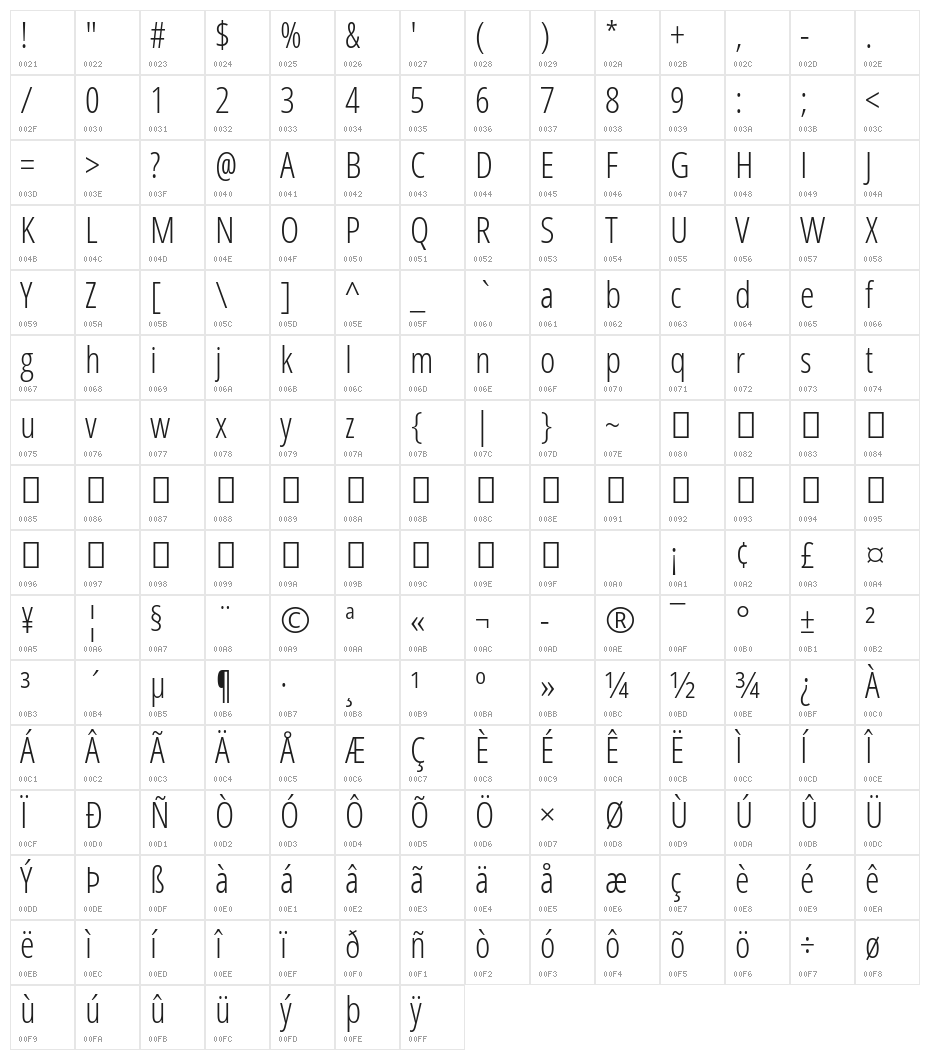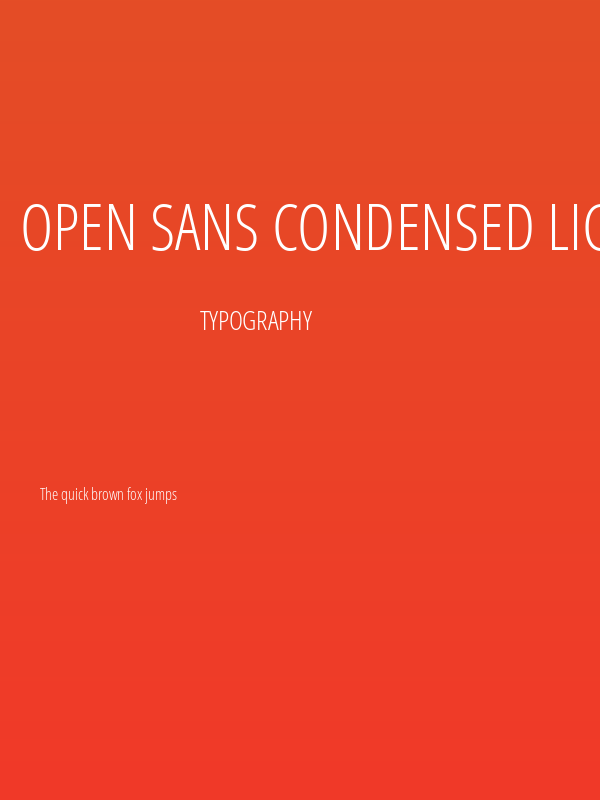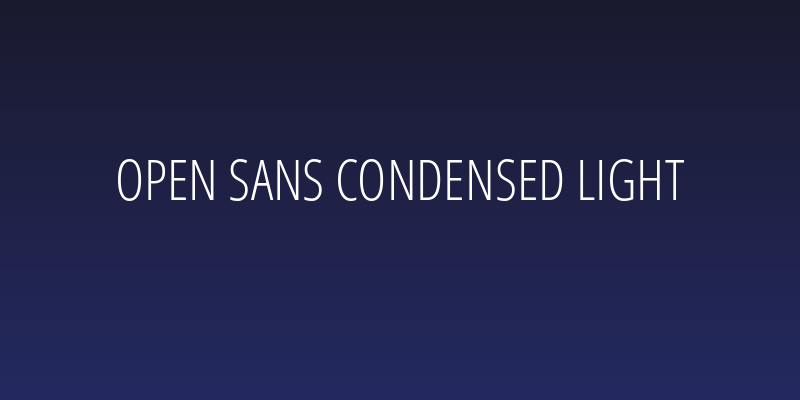
Open Sans Condensed Light Font
| Anwendungsfall | Headlines, Body text, Logos |
| Vorgeschlagene Projekte | Ideal for websites, mobile apps, branding, and editorial design where space efficiency and clarity are essential. |